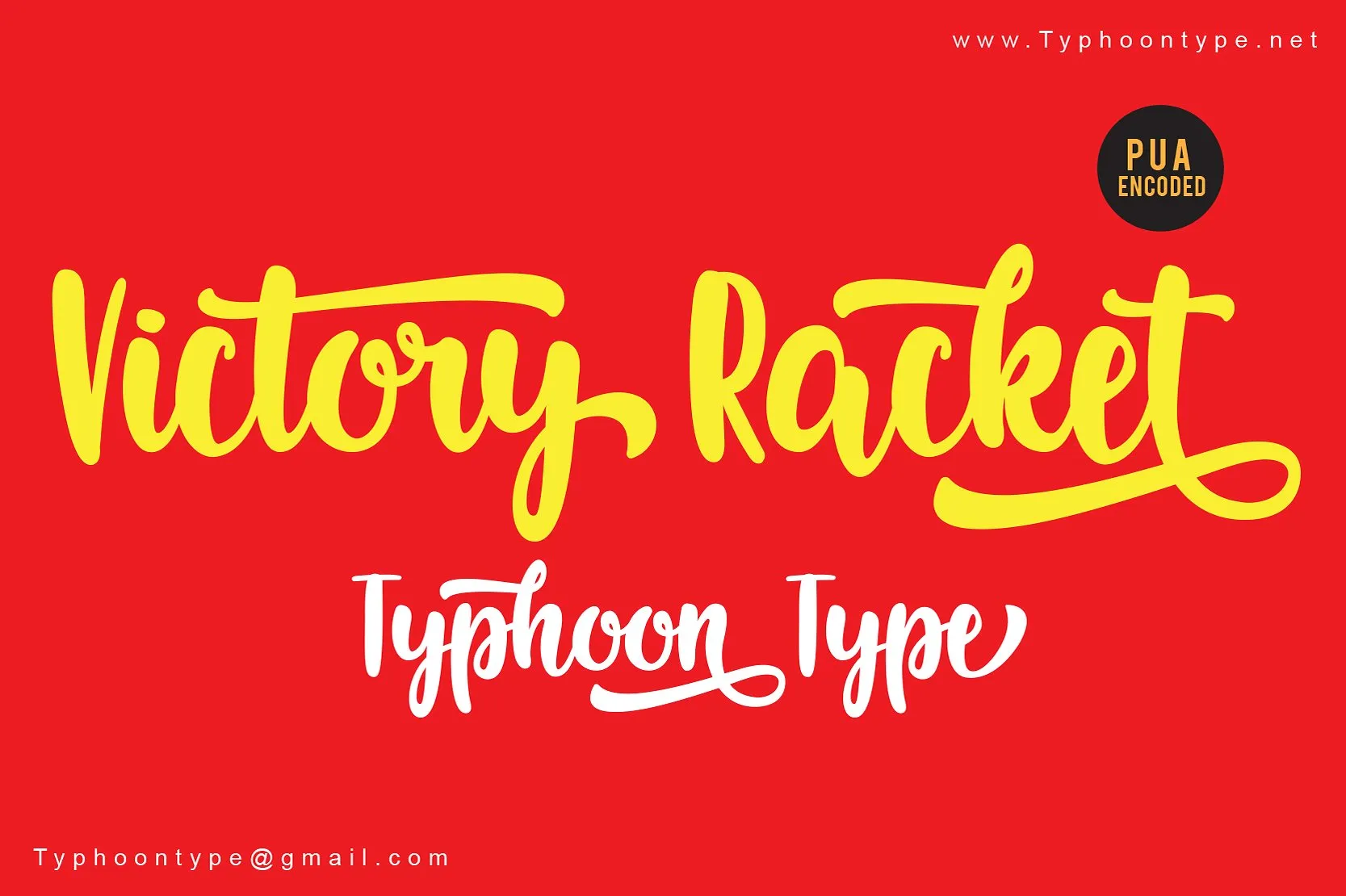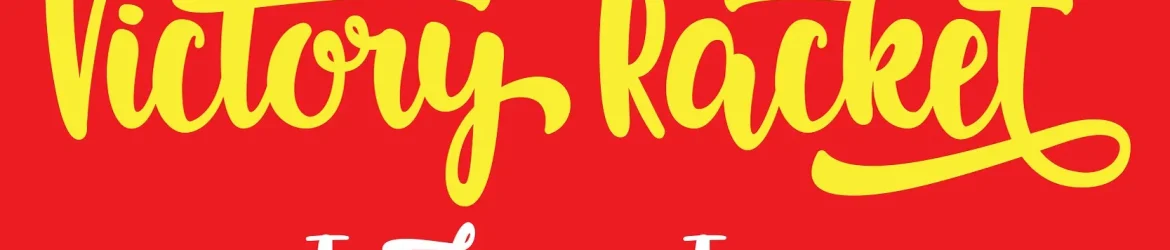
Victory Racket Script Font – Download Grátis
Venha conhecer a Victory Racket Script Font, uma elegante escolha para aqueles apaixonados por tipos de escrita. Desenvolvida pelo designer TyphoonType – S. Srisopha, esta fonte script moderna é perfeita tanto para uso digital quanto em trabalhos impressos. Com um estilo vibrante e orgânico, essa tipografia se destaca como uma maneira criativa de expressar sua identidade visual. Ideal para uso em aplicativos móveis, interfaces do usuário, sites e até mesmo outdoors, a Victory Racket mantém seu próprio estilo único em formas compactas e precisas. Seja você um designer digital ou gráfico, essa fonte oferece os melhores caracteres para complementar qualquer layout, tornando-a uma opção inestimável para quem busca expressar sua identidade de maneira única e moderna. Aproveite o seu potencial em criar textos exibidos, personalizando assim qualquer projeto que precise de um toque a mais de criatividade e originalidade.